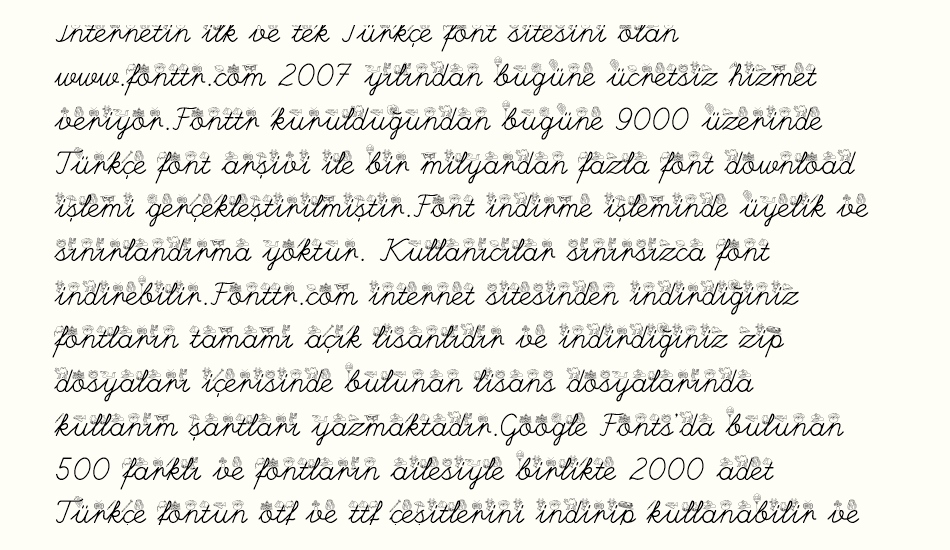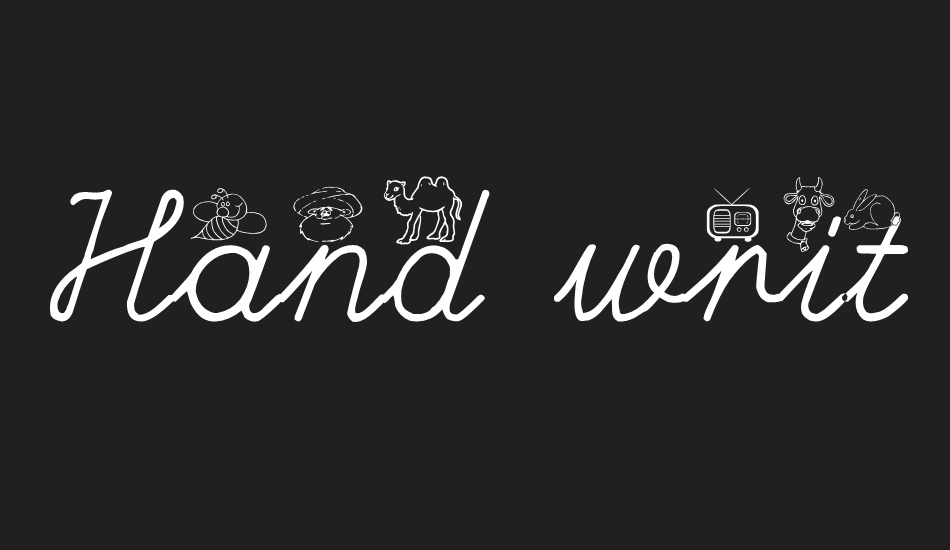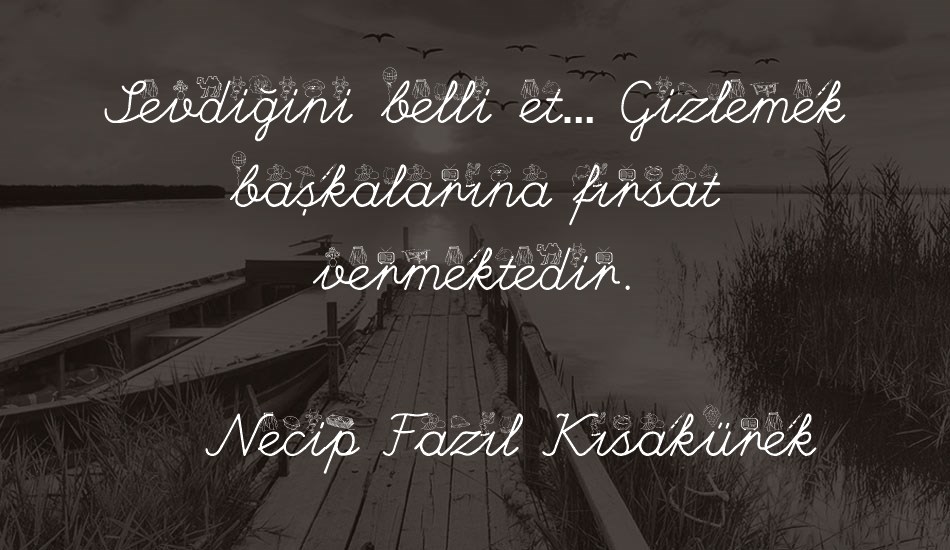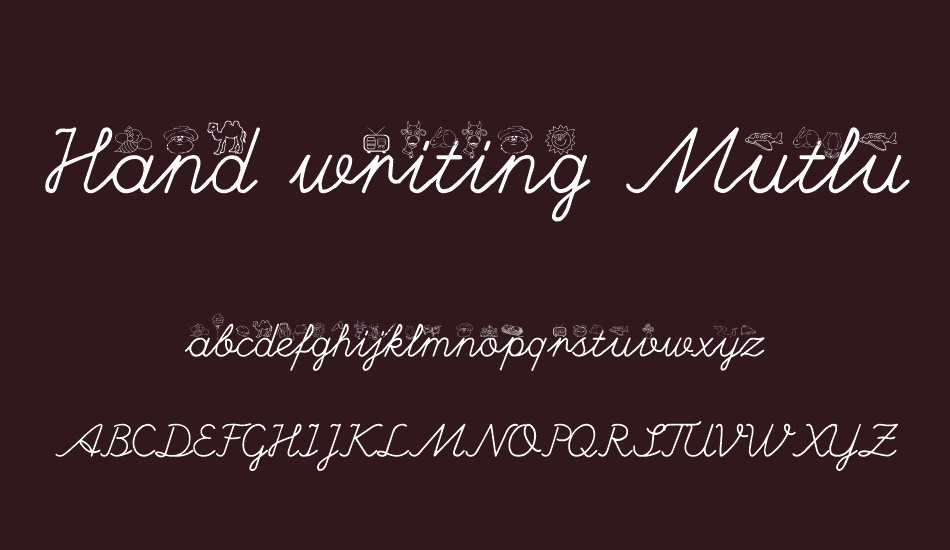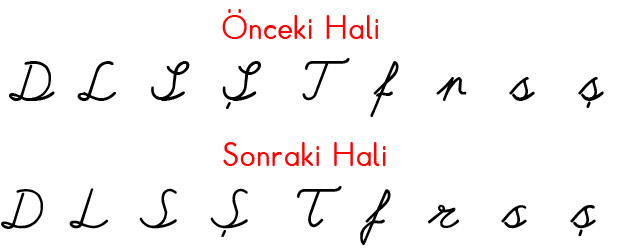
Hand writing mutlu font
2016-2017 öğretim yılında düzenlenen 5 adet YENİ EĞİK YAZI FONTLARI zip dosyası içerisine eklenmiştir
İlkokul yazı fontu 8 farklı seçeneğiyle indirebilirsiniz.
Okullarda kullanılan el yazısı fontu ve ilkokul 1 sınıflar için hand writing mutlu el yazısı fontu,